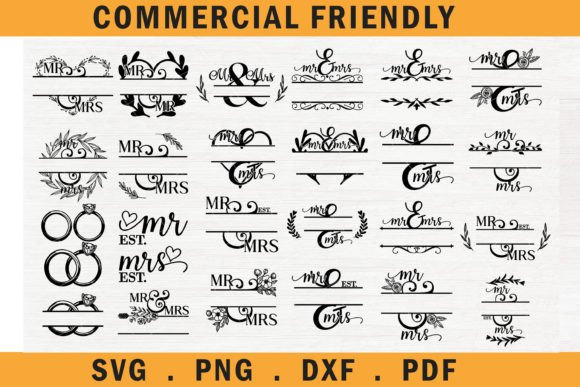
Mr and Mrs Monogram Bundle SVG,wedding
Die richtigen Designelemente zu finden, kann eine Herausforderung sein, aber Mr and Mrs Monogram Bundle SVG,wedding bietet eine außergewöhnliche Sammlung, die Ihre Arbeit sofort aufwertet.
Egal, ob Sie POD-Produkte (Print on Demand), Hochzeitseinladungen oder Social-Media-Grafiken erstellen, Mr and Mrs Monogram Bundle SVG,wedding ist die ideale Wahl.